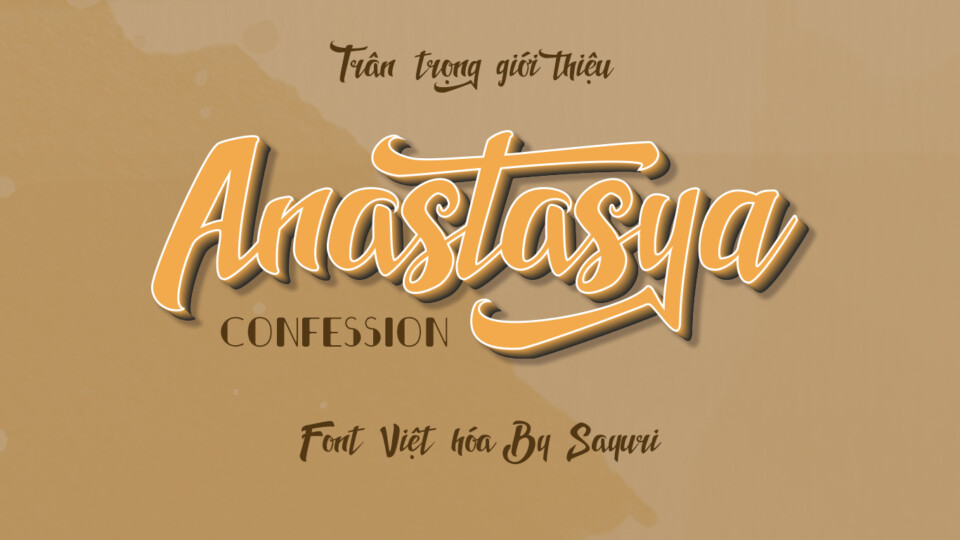
Font việt hóa Sayuri Anastasya Confession
Font việt hóa Sayuri Anastasya Confession – Nét chữ nghệ thuật tinh tế cho thiết kế sáng tạo
Giới thiệu về Font việt hóa Sayuri Anastasya Confession
Trong thế giới đồ họa hiện đại, việc lựa chọn một Font Miễn Phí chất lượng đóng vai trò then chốt giúp thông điệp của bạn trở nên nổi bật và thu hút hơn. Font việt hóa Sayuri Anastasya Confession là sự kết hợp hoàn mỹ giữa phong cách Script viết tay bay bổng và sự sang trọng, hiện đại. Được tối ưu hóa hoàn toàn cho ngôn ngữ tiếng Việt, bộ font này loại bỏ hoàn toàn các lỗi hiển thị dấu câu khó chịu, giúp các bạn học sinh và giáo viên dễ dàng ứng dụng vào các bài thuyết trình hay tài liệu học tập một cách chuyên nghiệp nhất.
Những đặc điểm nổi bật của Font việt hóa Sayuri Anastasya Confession
Thiết kế mềm mại và uyển chuyển
Đặc trưng của Font việt hóa Sayuri Anastasya Confession nằm ở những đường nét thanh mảnh, uốn lượn mang đậm dấu ấn cá nhân. Các ký tự được chăm chút tỉ mỉ, tạo cảm giác như những nét bút lông thủ công mềm mại trên trang giấy. Đây là lựa chọn lý tưởng cho những dự án cần sự lãng mạn, nhẹ nhàng nhưng vẫn giữ được nét thanh lịch cần thiết.
Tính ứng dụng đa dạng trong thực tế
Với bộ Font việt hóa Sayuri Anastasya Confession, bạn có thể tự do sáng tạo từ thiệp mời, bìa sách, nhãn dán đến các tiêu đề báo tường trong trường học. Sự linh hoạt của font chữ này giúp các nhà thiết kế không chuyên cũng có thể tạo ra những tác phẩm ấn tượng mà không mất quá nhiều thời gian căn chỉnh kỹ thuật.